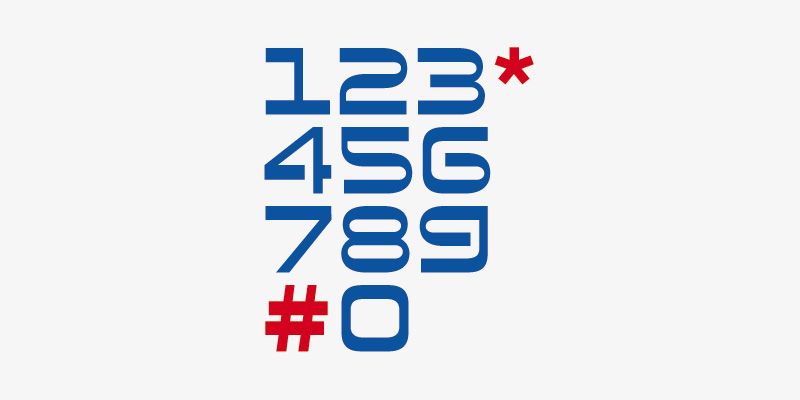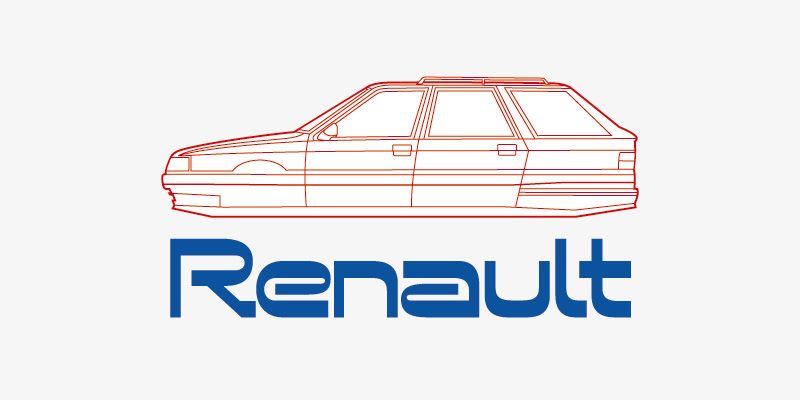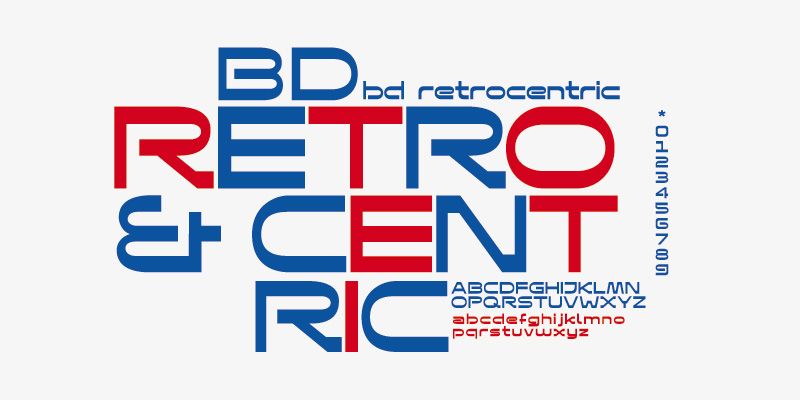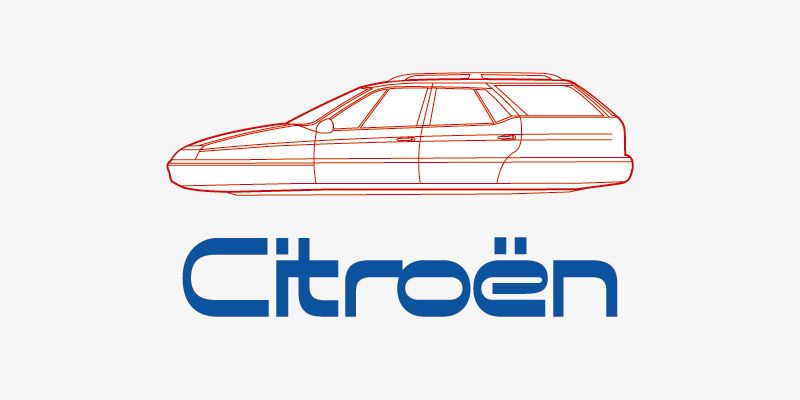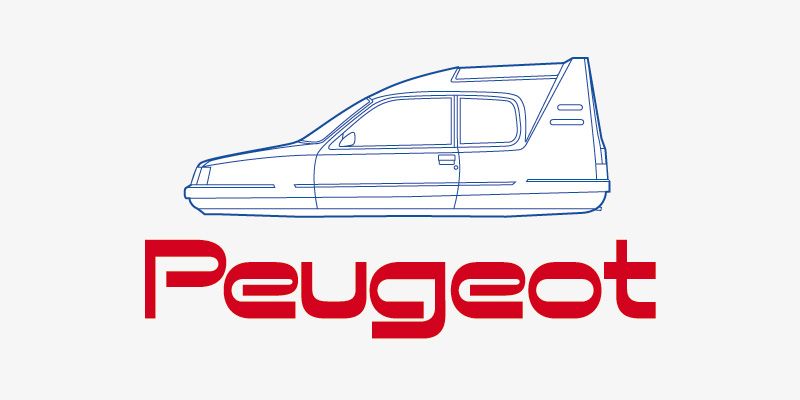
BD Retrocentric s’inspire des logotypes créés dans les années 60 et 70. Il s’agit d’un mélange équilibré de rétro et de futurisme. Conçu par Lopetz en 2009.